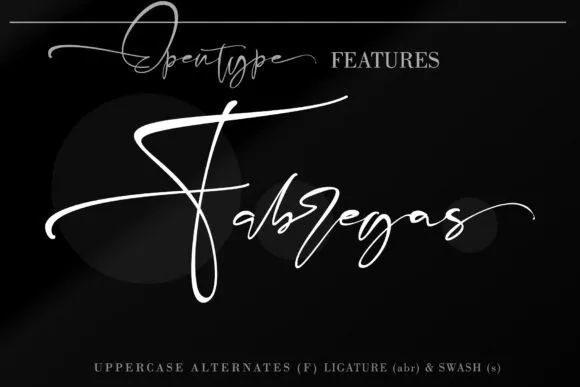
Fabregas Script Font – Download Grátis
A fonte “Fabregas Script” é uma elegante escolha para projetos que valorizam a autenticidade e o estilo moderno. Desenvolvida por C00zona, esta fonte moderna mantém as formas únicas da calligrafia contemporânea. Ela foi criada de forma manual, resultando em uma linha de escrita natural e sofisticada que se encaixa perfeitamente para diversas aplicações gráficas. Além disso, “Fabregas Script” é um traço de assinatura handwritten projetado para dar vida à suas ideias criativas. Suas linhas fluidas e estilo único são uma ótima escolha tanto para títulos, assinaturas, logotipos quanto para convites casamentos, camisetas, cartões de endereço, rótulo, notícias, panfletos e até mesmo estandarte. A “Fabregas Script” é uma fonte perfeita para quem busca um toque único em qualquer projeto visual.